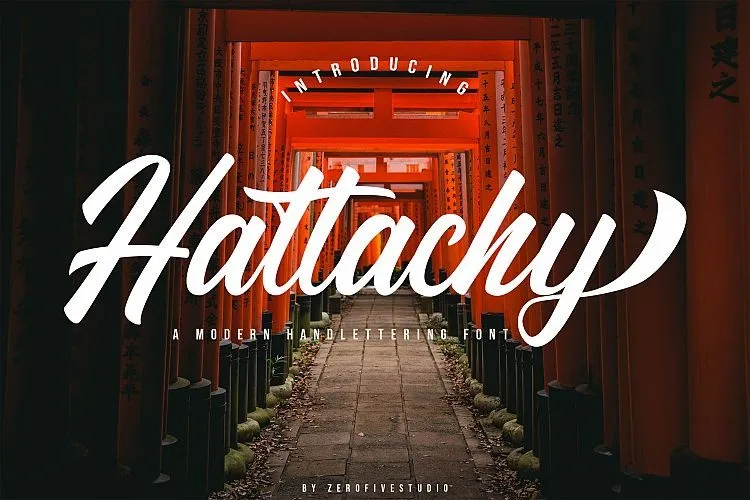
Hattachy Modern Script Font – Download Grátis
Olá amigos, estamos ansiosos para compartilhar com vocês a Hattachy Font Modern Script, uma opção versátil para designers. Esse tipo de letra moderna e elegante é perfeito tanto para usar sozinho quanto juntos, tornando-o um recurso indispensável para todos os tipos de projetos gráficos. Introduzimos a Hattachy Font: um estilo arrojado e inovador para tipos escritos à mão. Foi criado com uma intenção clara em mente – oferecer uma opção perfeita para produtos diversos, desde logotipos e selos até embalagens de produtos e design gráfico. Perfeito tanto para criar um novo projeto empresarial ou designer, quanto para adaptar a estética dos seus projetos finais. A Hattachy Font é uma escolha ideal para qualquer tarefa que exija o toque único e autêntico do texto à mão escrita. Seja ela parte integrante de seu design de marca, o título das suas postagens no Facebook ou Instagram, da sua campanha de marketing digital ou até mesmo as etiquetas dos seus produtos finais – a Hattachy Font Modern Script tem seu espaço em todos esses projetos. Com certeza, seja você um designer de sites, artista gráfico, criador de conteúdo digital ou simplesmente alguém que gosta de adicionar um toque especial às suas criações digitais com uma pitada de personalidade à mão – a Hattachy Font Modern Script tem algo para todos.